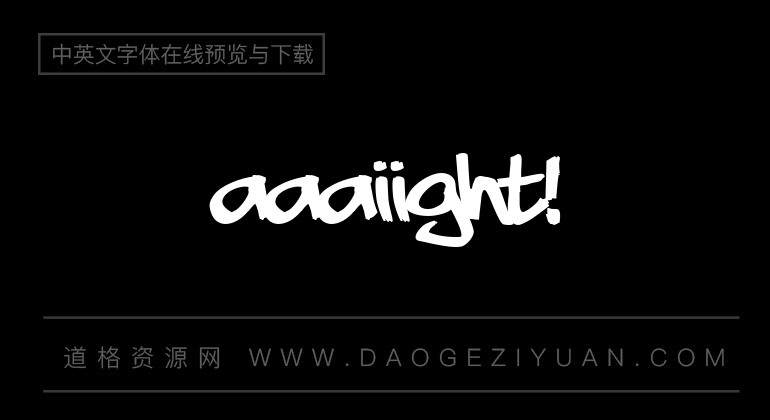
吗? Aaaiight!是一款由Font Diner推出的手写体字体,它具有活泼、清新、活力的设计风格,适合用于各种设计和印刷工作。它的字形有着强烈的立体感,每个字母都有自己独特的特点,比如字母a有着细长的尾巴,字母e有着粗大的笔画,字母f有着双层结构。Aaaiight!字体还有着浓厚的乡村风格,能够给文字带来一种活泼、清新、有趣的感觉,适合用于各种海报、T恤、书籍封面等设计工作。内容介绍
Aaaiight!是一款非常不错的手写艺术字体,具有很好的视觉感,适合于文化类的宣传设计、商业类品牌的广告和产品包装设计以及个性化文字排版等较多场景。